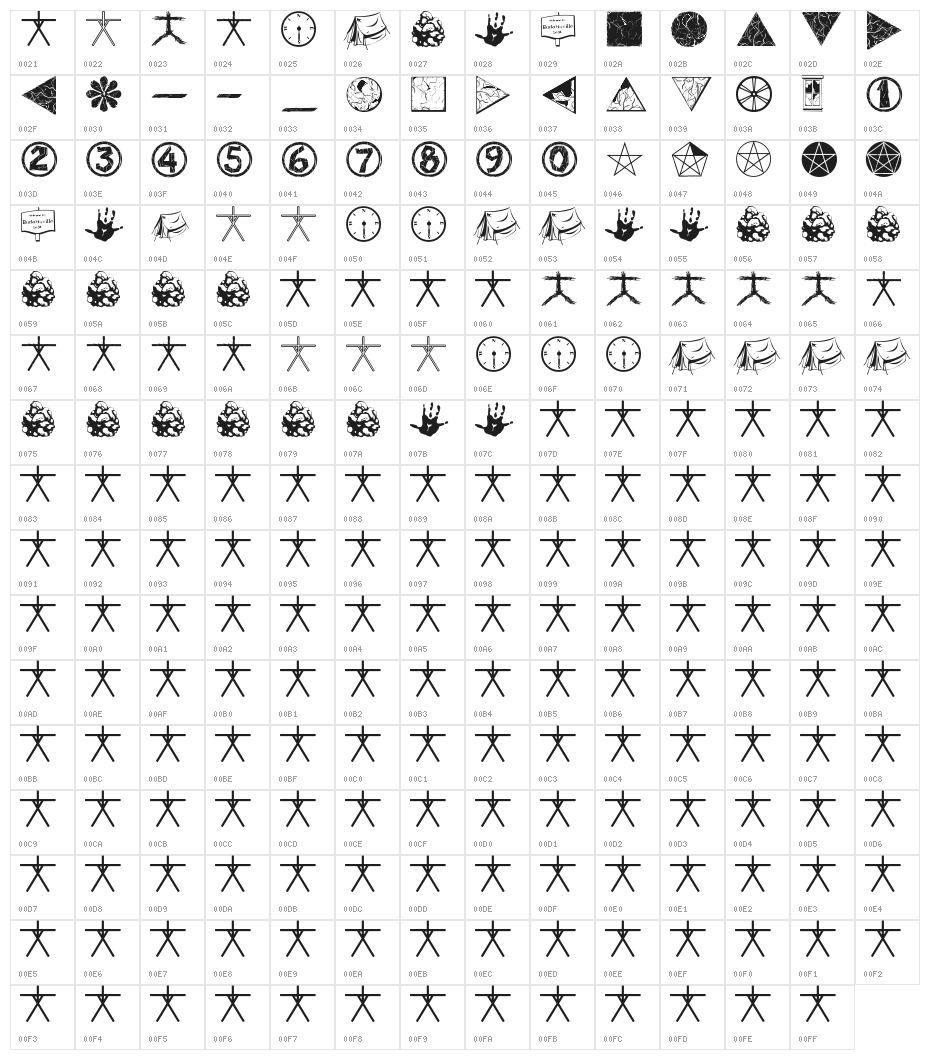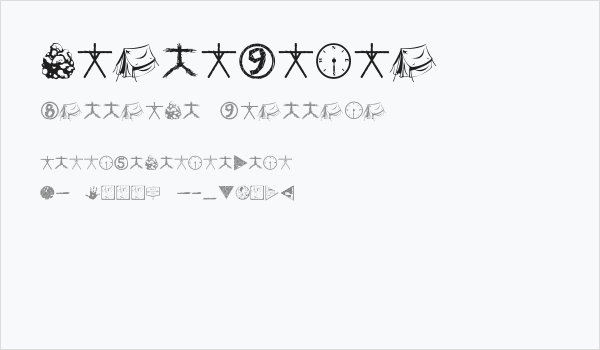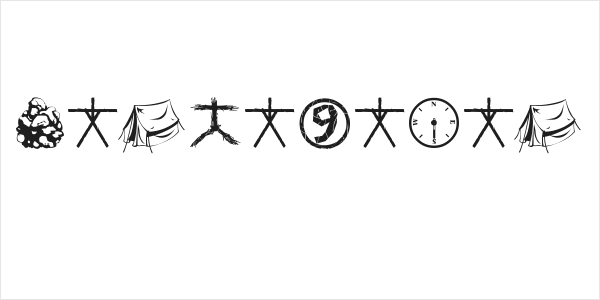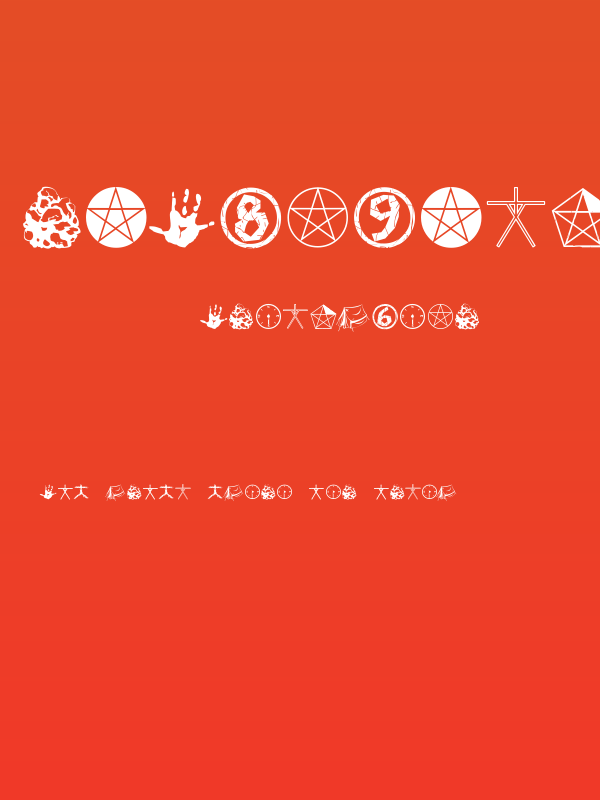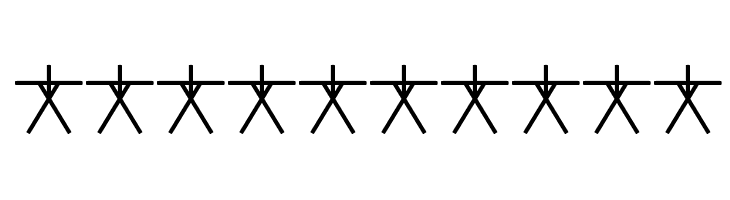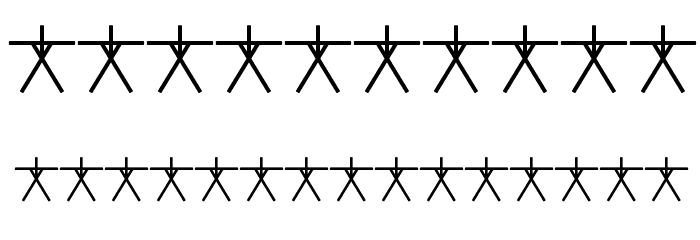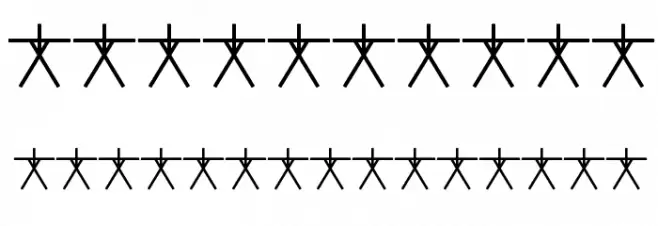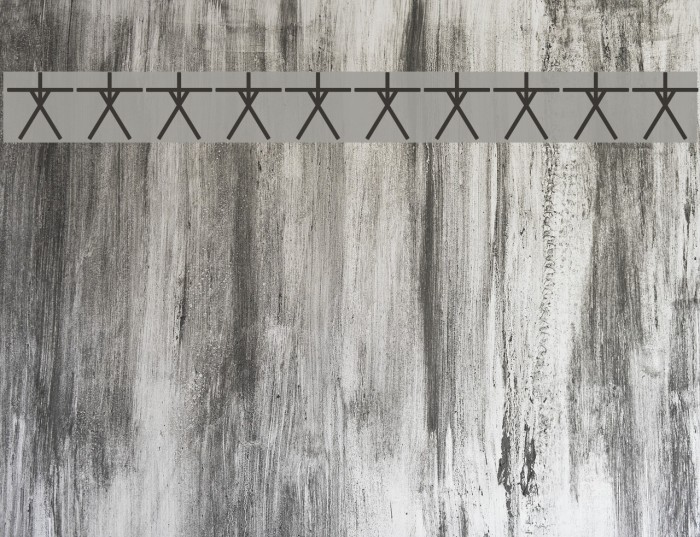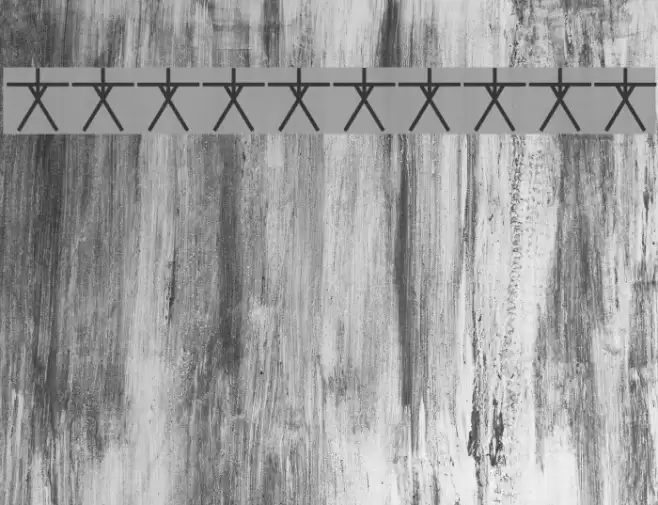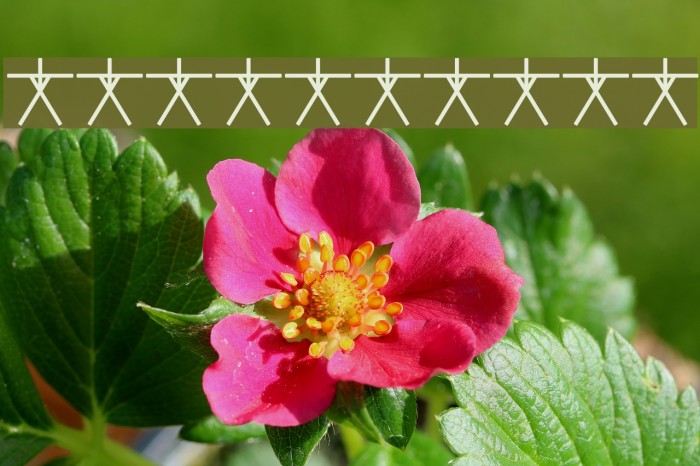
WitchDings Font
| Anwendungsfall | Decorative elements, Themed designs |
| Vorgeschlagene Projekte | This pattern could be used for decorative borders, Halloween-themed designs, or as a graphic element in creative projects. |